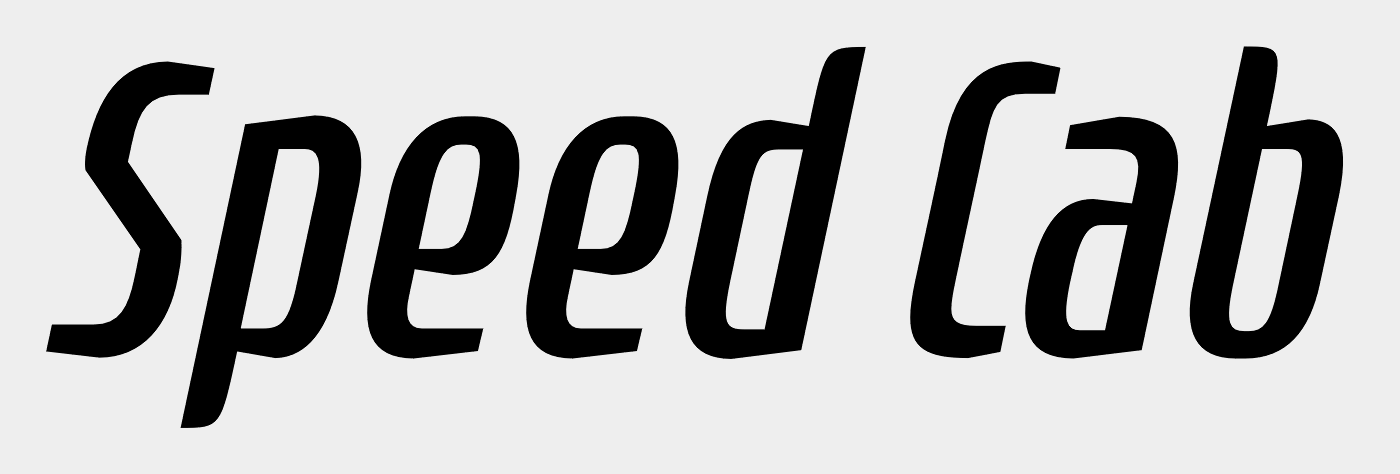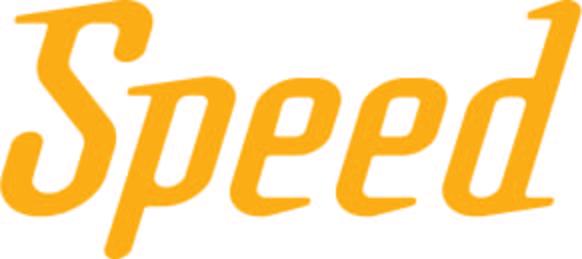
Bitte dringend um Hilfe (Speed)
Unser Webdesigner ist leider in Konkurs gegangen und hat uns nicht die Daten und Schriftarten unseres Logos übermittelt.
Kann mir bitte jemand helfen und diese Schriftart bestimmen.
Zumindest konnte ich so (mit den üblichen Identifikationsmethoden) erstmal nichts finden.
Beiden Websites kann ich leider keine Informationen zur Schrift vom Logo entnehmen (hätte ja sein können, das zum  Beispiel alle h1 Überschriften in dieser Schrift geschrieben sind.)
Was ich mir aber vorstellen könnte ist, dass die Serifen ursprünglich gar nicht an der Schrift selbst waren, sondern vom Logodesigner, in diesem Fall eurem Webdesigner, händisch angefügt wurden und die Schrift leicht verändert wurde.
Meiner Theorie nach könnte diese "Ausgangsschrift" die Rogue Sans Cond Light sein:
ahhhhhh die konnt sehr nahe.
ja hab ich mir auch schon fast gedacht, dass er das zusätzlich noch geändert hat.
da scheinen noch mehr Schriften gespeedlined worden sein ...
wäre ja schade mit einer nur halbwegs passenden Schrift weiter zu machen
"Speed Creative" ist aus der von Designfreak empfohlenen Rogue generiert worden – das mag wohl auch die gleiche Adresse erklären.
die alte Schrift kommt mir irgendwie bekannt vor, weiß aber nicht woher
Tatsächlich. Das wusste ich auch nicht vorher :-?.